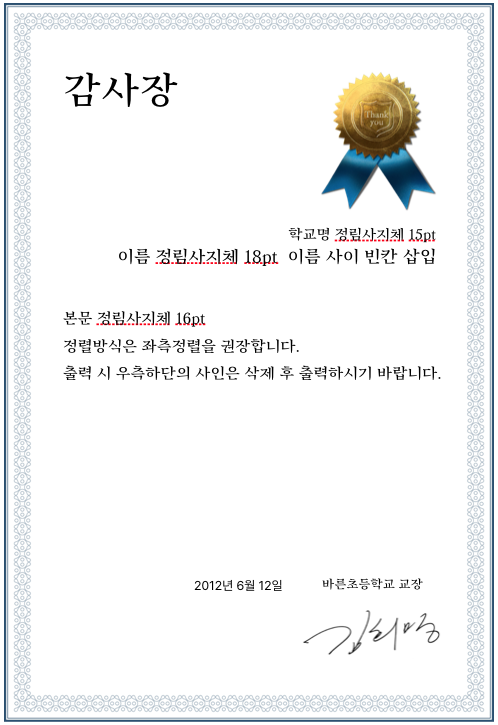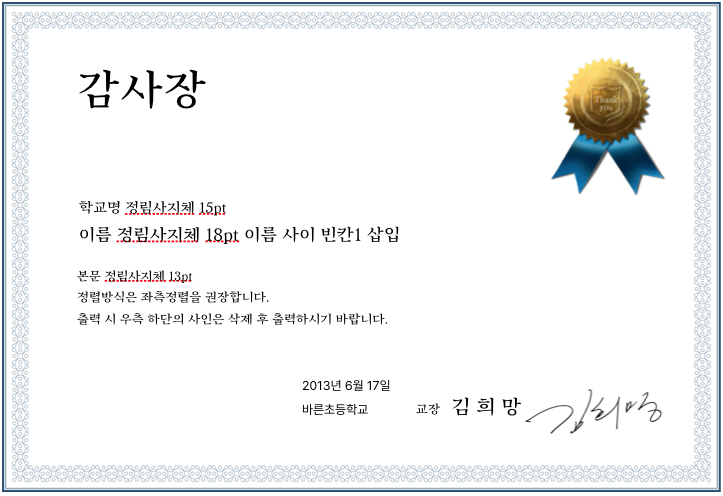
서체 활용 사례
Font In Use
다양한 서체 활용 사례를 보여드립니다
상황과 용도에 잘 맞는 글꼴을 선택하여 원하는대로 다양하게 활용할 수 있습니다.
여러분의 이야기를 담아 자유롭게 표현하고 활용해 보세요.
부여 서체 활용 최신 사례
신동엽 손글씨 서체, 정림사지 서체를 활용한 최신 사례들을 살펴봅시다.
포스터, 굿즈부터 공공 디자인까지 다방면으로 활용 가능하며 부여 서체만의 고유의 분위기를 통해 원하는 방향의 디자인을 만들어보세요.
해당 템플릿 제공은 부여 서체, 신동엽 손글씨 서체에 최적화되어 만들어졌습니다.